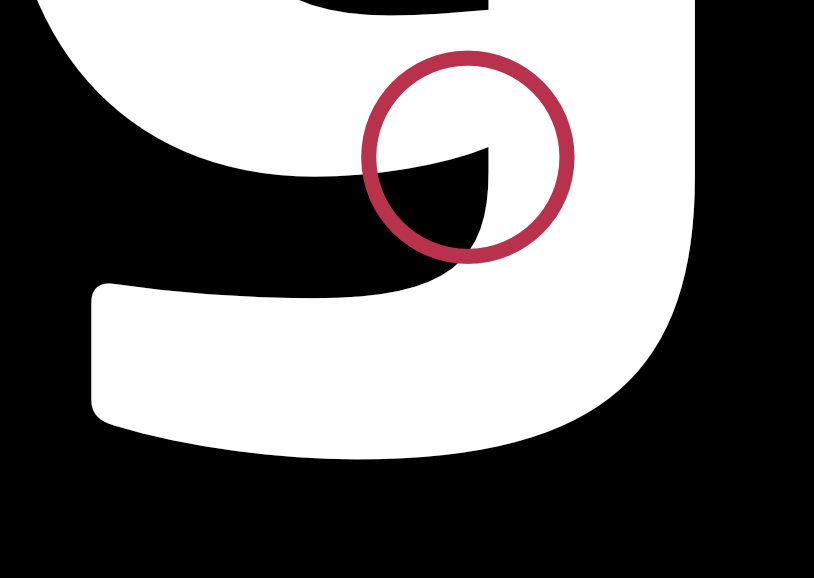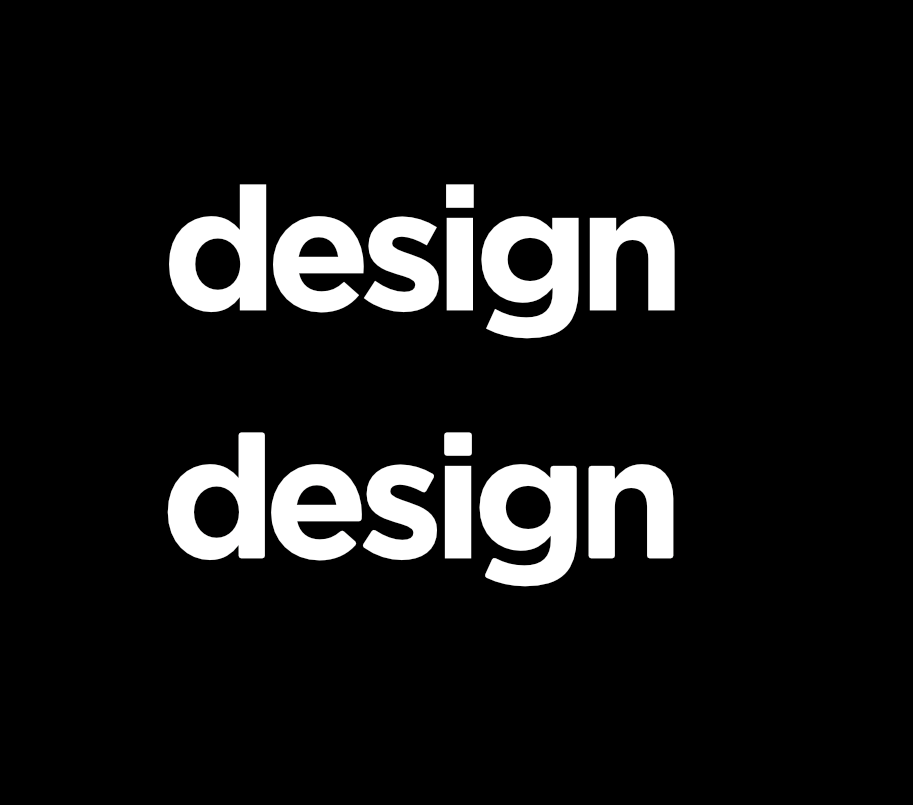
Eine eckige Schrift abrunden
spricht eigentlich was dagegen, bei Fonts eigenständig Abrundungen zu machen um die Typo bspw. an eine Grafik anzupassen? Gibt es da gewisse Dinge, auf die man achten sollte oder einfach nach Augenmaß bzw. eigenem empfinden. Mit Konturen die Strichstärke verändern ist ja z. B. nicht empfehlenswert.
Beispiel: Oben Gotham original unten Gotham manuel abgerundet.
Mit allen Ecken sind aber nur die Ausläufe gemeint oder auch die Binneninnenräume, wie hier beim G?
Solange es allen Ecken gleichmäßig zugewiesen wird, spricht nichts dagegen. Das entspricht dem Prinzip vieler Rounded-Schriften. Nur die teilweise Hinzufügung solcher Rundungen an manchen Ecken (wie oft in Logos praktiziert) geht gar nicht.
Hallo, wieso „geht gar nicht“?
Die Aussage ist mir zu absolut. Ohne ein Beispiel zu kennen, sind die „Regeln“ bei der Logo-Gestaltung doch ziemlich weit gefasst. Ich kenne zumindest keine, die so eine „Schriftmanipulation“ verbietet.
Weil Schrift von Schreiben kommt. Moderne Druckschriften sind zwar in aller Regel nicht mehr tatsächlich schreibbar, benutzen aber – wie oben schon angedeutet – weiterhin das Prinzip eines buchstabenübergreifenden, konsistenten Strichverlaufes auf Basis eines gedachten Schreibwerkzeugs, das Strichstärkenänderung, Kanten, Strichenden, Serifenform usw. diktiert. Das gilt für alle Schriftsysteme, Schriftstile und selbst experimentelle Schriften halten sich oft sogar an dieses Grundprinzip. Und wenn man von so einem Grundprinzip, an welches man durch das Lesen Tausender Texte und Schriften gewöhnt ist, abweicht, dann wirkt es halt schnell mindestens unnatürlich (wenn nicht gar »falsch«). Bei Logos auf Basis von Satzschriften ist es die klassische Verschlimmbesserung. Die vorhandene Konsistenz wird mutwillig zerstört und ein unnötiger schriftgestalterischer »Fehler« hinzugefügt. Wäre auch nicht anders, als jetzt zum Beispiel das enthaltene Kerning so zu ändern, dass eine deutliche, unerwartete Lücke die Gleichmäßigkeit der Weißräume zerstört. Ob solche Dinge im »Großen Buch im objektiven Logo-Regeln« auftauchen oder nicht sei dahingestellt. Aus Sicht eines aktiven Schriftgestalters erlaube ich mir Weitergabe solcher/unserer Prinzipien in dieser Deutlichkeit.